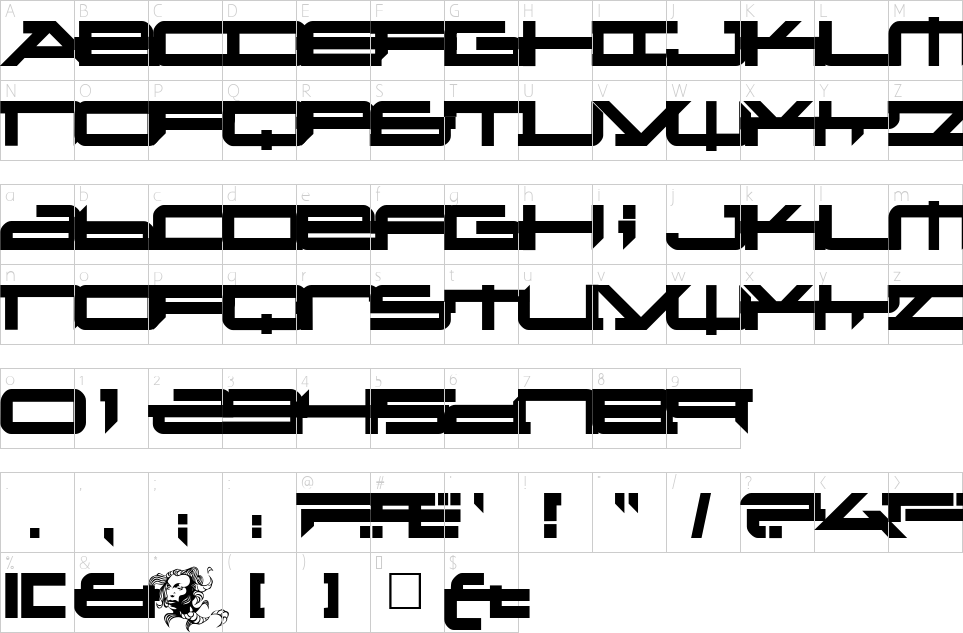
A Metatron Font é uma elegante e versátil fonte que adiciona um toque único a qualquer projeto gráfico. Desenvolvida por Chaos Fonts, esta fonte oferece um conjunto amplo de caracteres, incluindo letras gregas e símbolos, que criam um efeito visual inovador. Com sua interface simples e intuitiva, a Metatron é ideal para designers que procuram uma fonte moderna para uso em websites, logotipos e textos gráficos. Com uma baixa quantidade de downloads de 3.507, essa fonte gratuita é uma opção valiosa para projetos residenciais ou comerciais. Engaje seu público com estilo e sofisticação, escolhendo a Metatron para personalizar seus trabalhos.